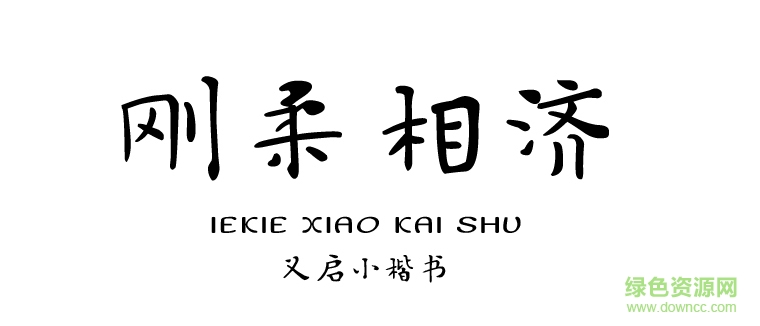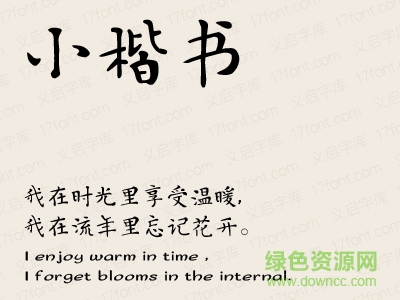
義啟小楷書是一款非常漂亮的楷書字體,這款字體端正中帶著些柔情似水,看起來很舒服,整體效果非常出色,喜歡的朋友歡迎來綠色資源網(wǎng)下載使用!
小楷,即是楷體小字。 義啟小楷書,是一款汲取歷代小楷特質(zhì)為基礎(chǔ)的書法字庫。而從現(xiàn)實效果上擺脫了書法字庫在小顯示屏上的弊端,主要在筆畫上做了改善。小楷的靈魂在于“小字如大字 ”,就是字小要有大字的氣象與章法。修飾筆畫在保證氣象的基礎(chǔ)下,變的圓潤簡潔,不至于顯示時出現(xiàn)不了效果反而糊掉,結(jié)構(gòu)上收放有度。